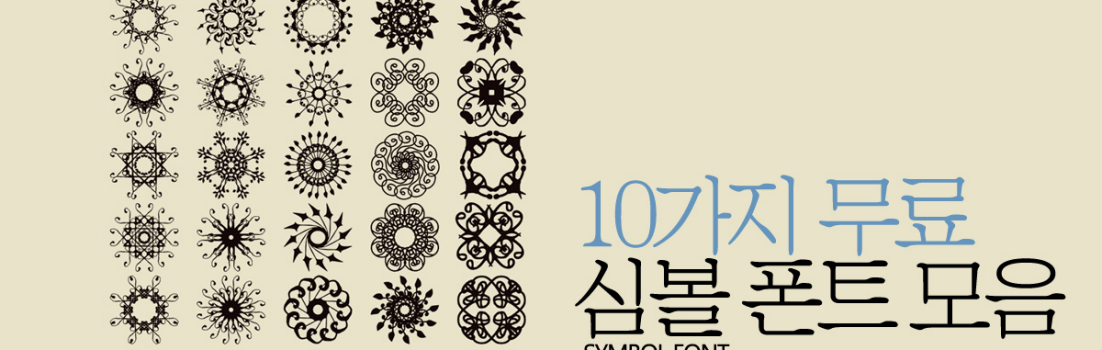
예쁜 심볼 폰트를 사용해 디자인 작업 시간을 단축시키자
오늘 소개할 자료는 아이콘 또는 디자인 요소로 쉽게 활용 가능한 심볼 폰트입니다.
총 10가지 무료로 사용 가능한 폰트로 어떤 디자인 작업에도 적용 가능합니다.
1. Web symbols
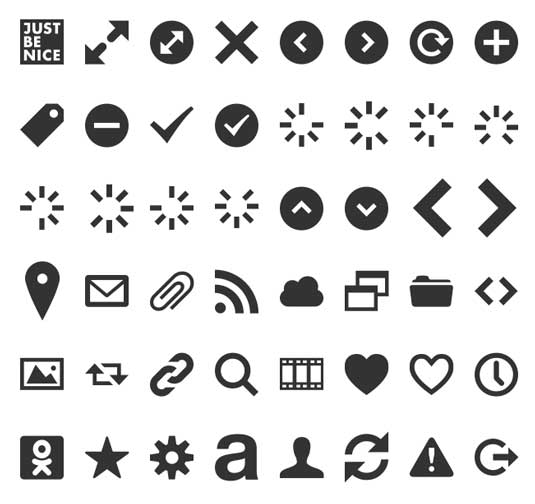
2. Heydings Common Icons
3. Efon
4. Kalocsai Flowers
5. Web Hosting Hub glyphs
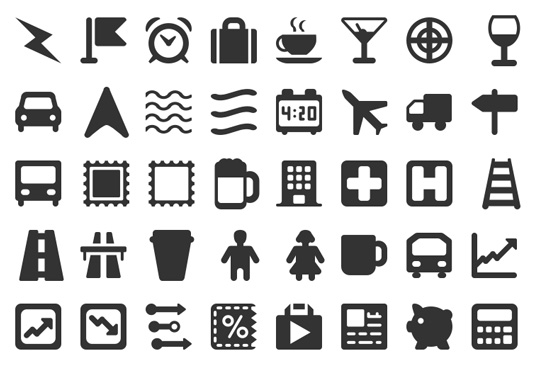
6. Symbol signs
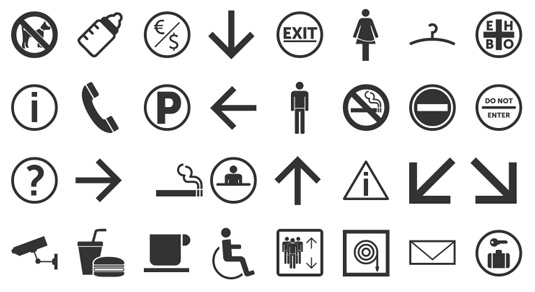
7. Dingbat Cobogó
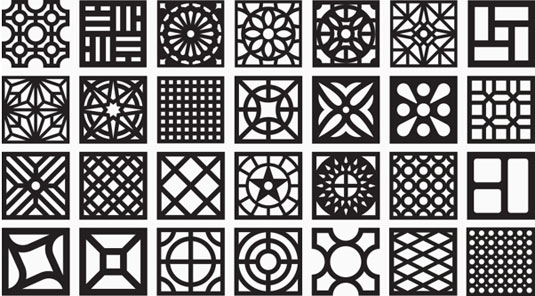
8. Notice
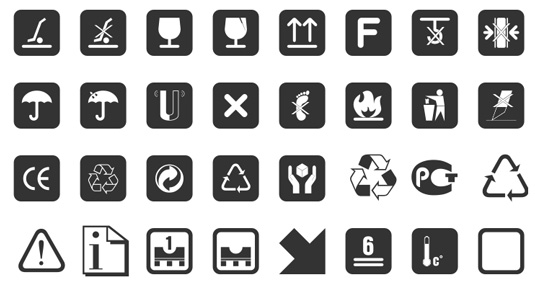
9. Rhomus Omnilots
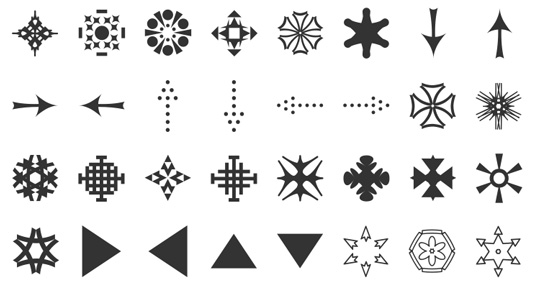
10. Rosette